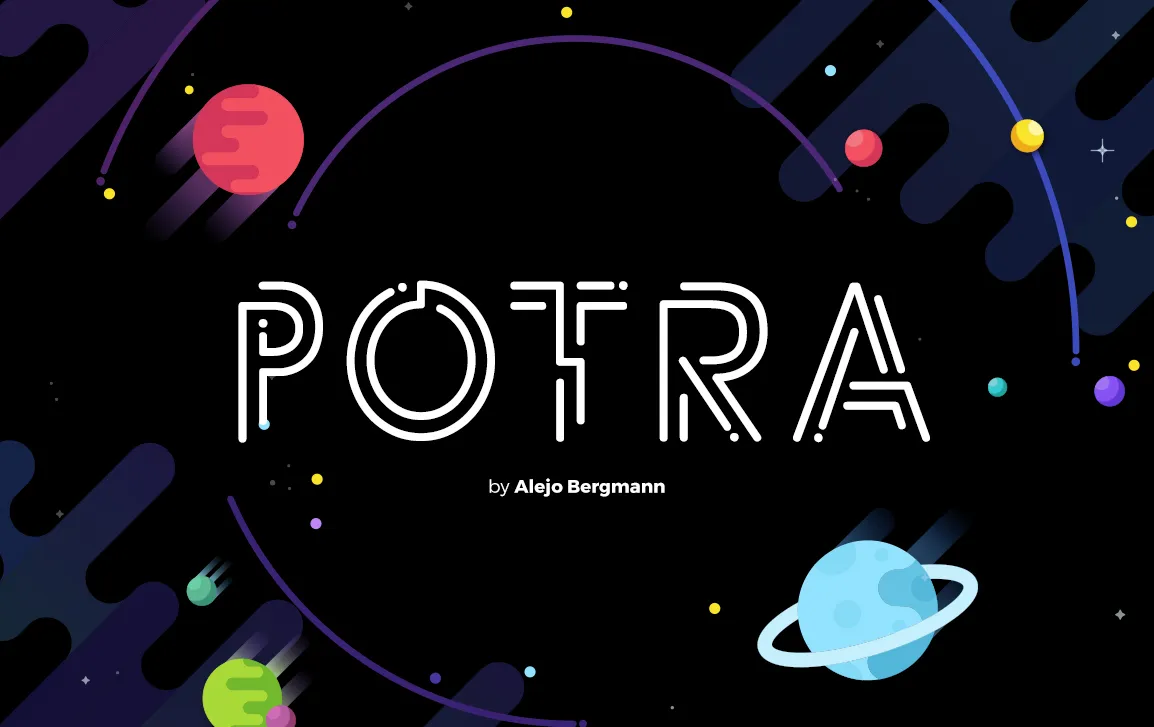
Potra Typeface é uma futurista tipografia exibicional criada por Alejo Bergmann. Com linhas redondas que remetem ao design de tecnologia avançada, esta fonte apresenta letras maiúsculas completas, números e símbolos. Ideal para múltiplas aplicações visuais, Potra é perfeitamente adequada para logotipos, selos e rótulos, headlines e bandeiras, bem como impressões de todos os tipos. Engana-se quem pensa que esta fonte é limitada a ambientes digitais – sua elegância moderna e linhas arredondadas oferecem uma ótima alternativa para projetos gráficos no papel também. Seja você um designer, artista ou editor de texto, Potra é uma escolha segura para qualquer projeto que valorize design e tecnologia moderna.